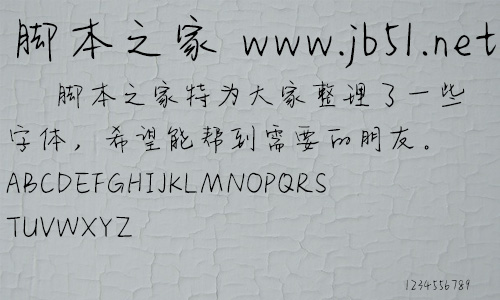
Aa苦海無(wú)涯回頭是我一款不錯(cuò)的藝術(shù)字體,這款字體筆觸較為纖細(xì),書(shū)寫(xiě)流暢,具有很好的視覺(jué)感,適合應(yīng)用于藝術(shù)設(shè)計(jì)、平面宣傳設(shè)計(jì)、網(wǎng)頁(yè)設(shè)計(jì),書(shū)法字帖等領(lǐng)域,喜歡的朋友快來(lái)下載使用吧!